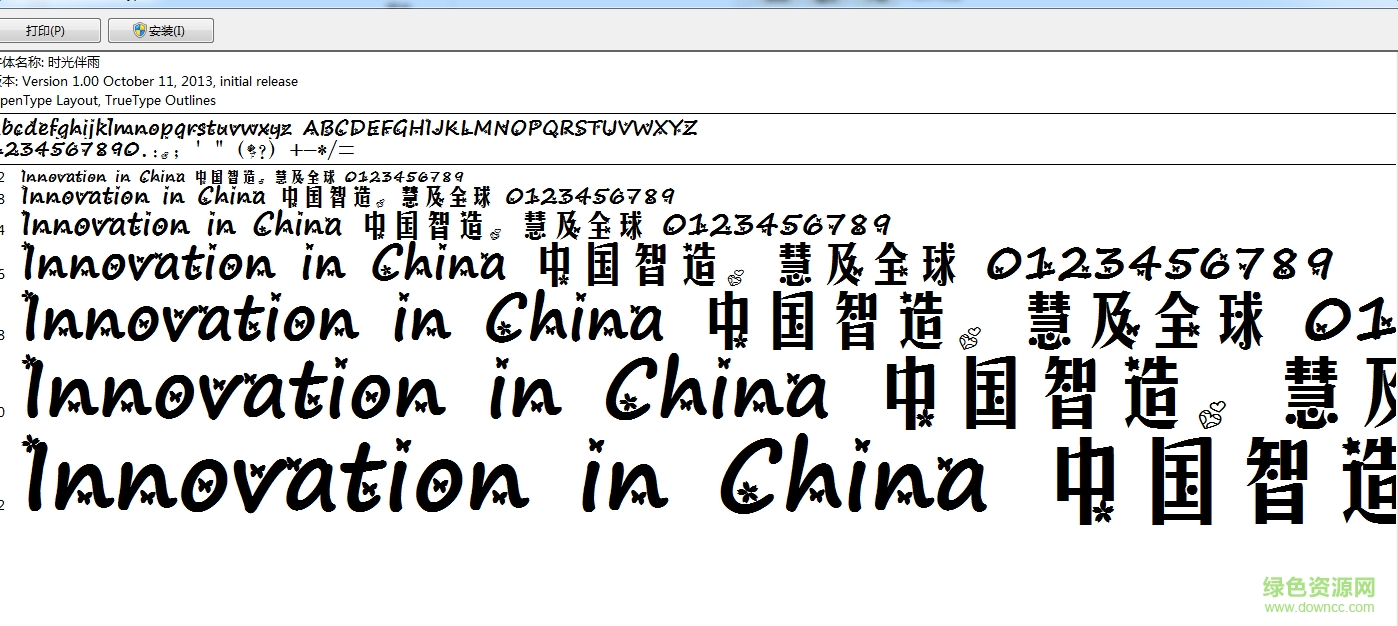
時(shí)光伴雨體字體
時(shí)光伴雨字體是一款藝術(shù)氣息相當(dāng)濃厚的個(gè)性字體,字體典雅規(guī)整,端正大氣、簡(jiǎn)介明了,藝術(shù)設(shè)計(jì)、海報(bào)設(shè)計(jì)、文字排版等領(lǐng)域都可以使用!喜歡的朋友趕緊來(lái)綠色資源網(wǎng)下載喲!